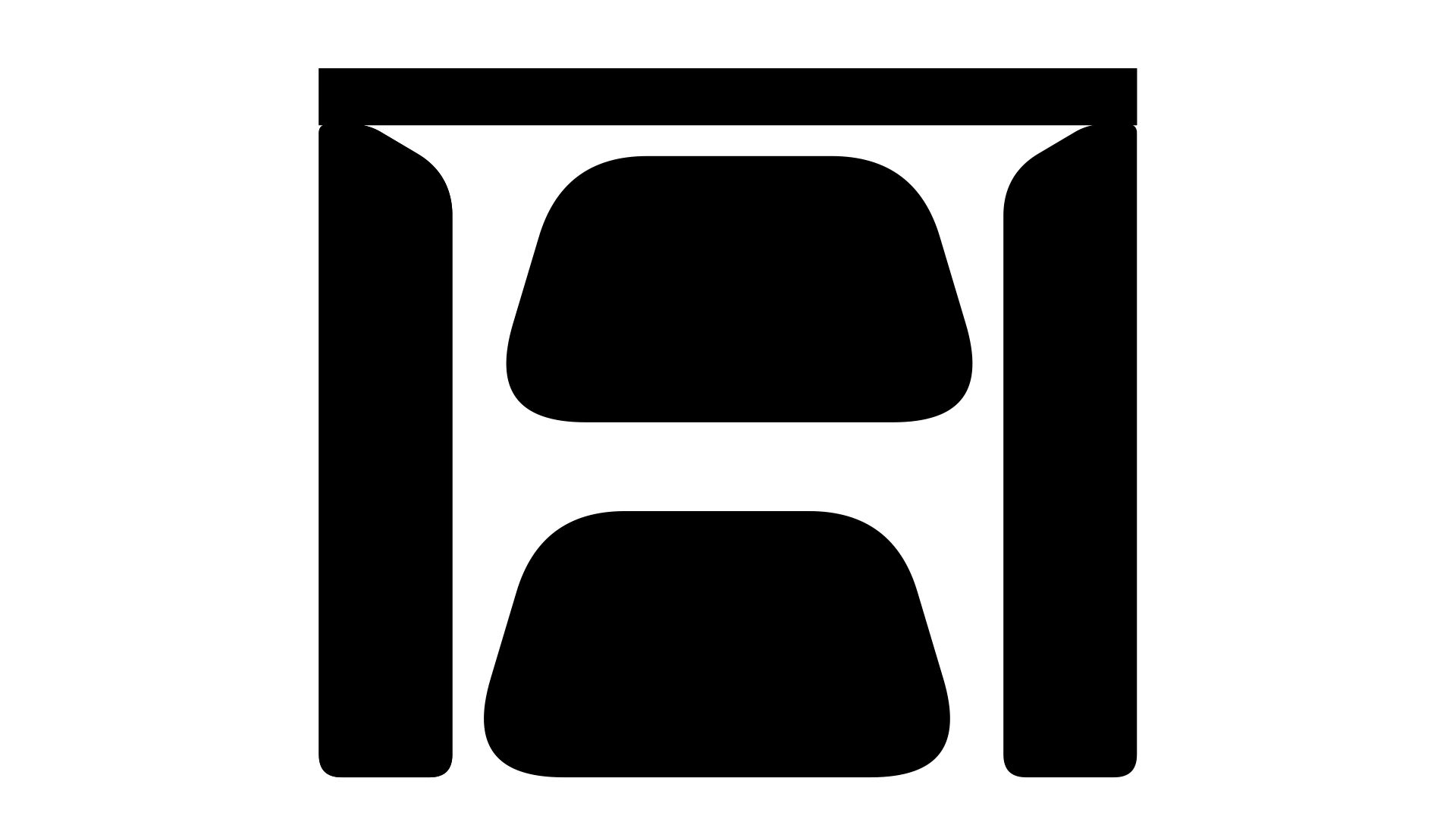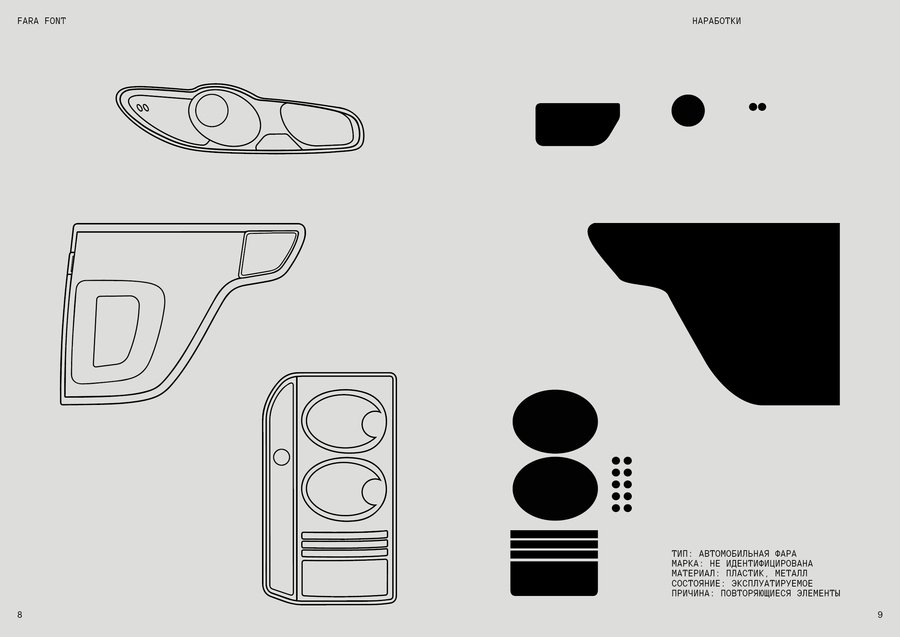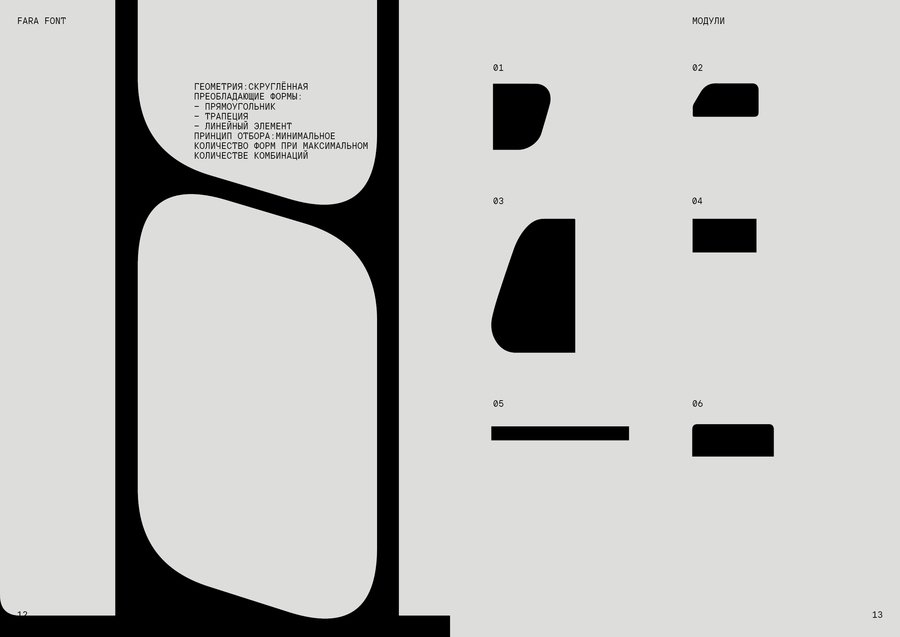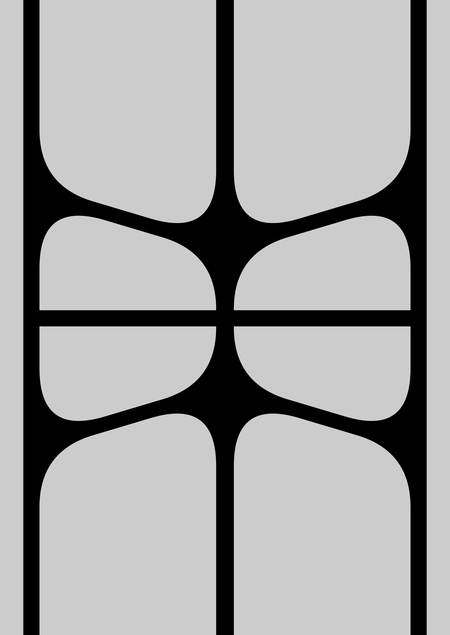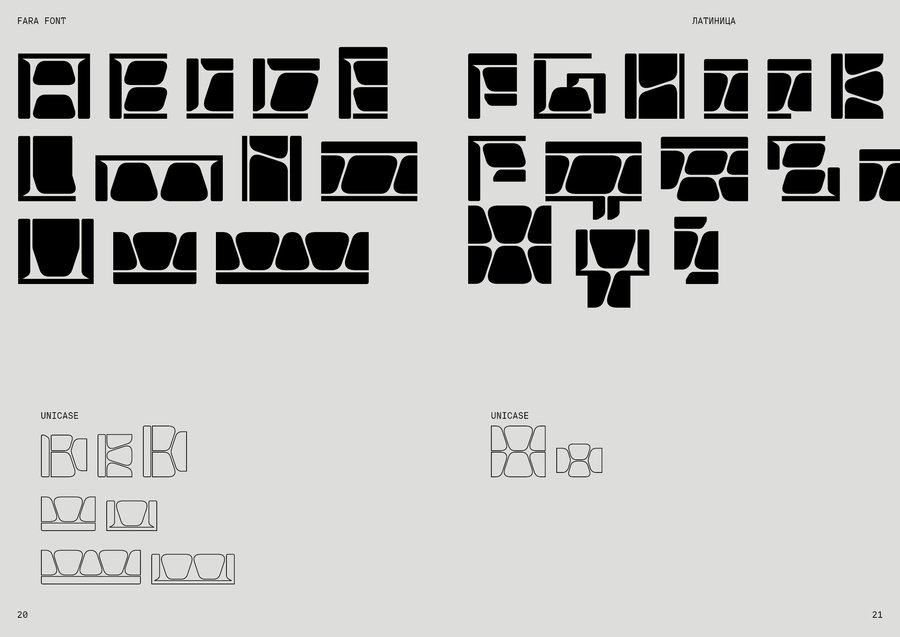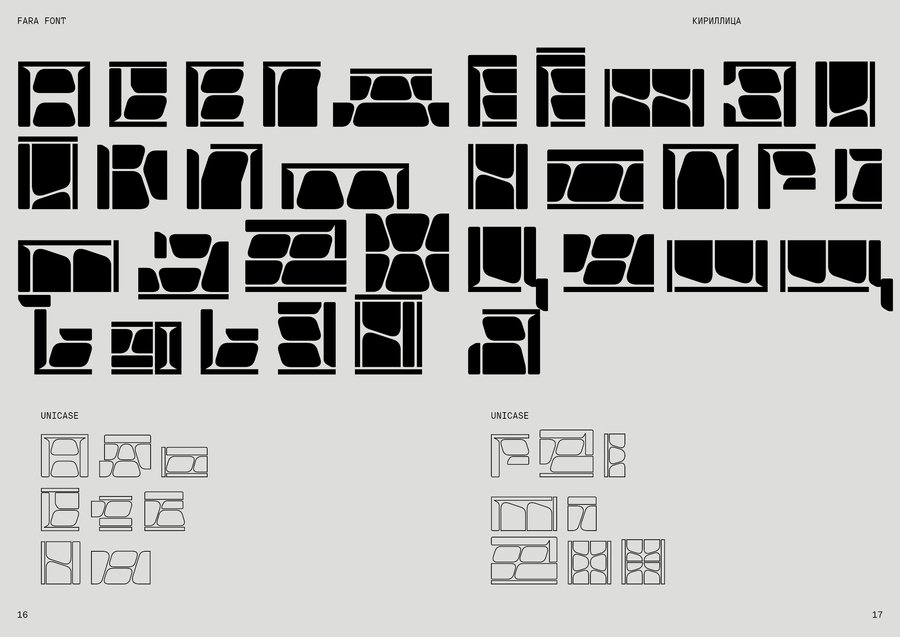
Объект: FARA FONT
Тип системы: модульная Источник: автомобильная оптика Метод преобразования: упрощение формы Количество элементов: 6 Тип соединения: модульный Ключевой параметр: контрформа
59.871561, 30.320092 Московский район
Расположение: регион 52, Санкт-Петербург Дата прогулки: 7 апреля 2026 Время старта: 18:03